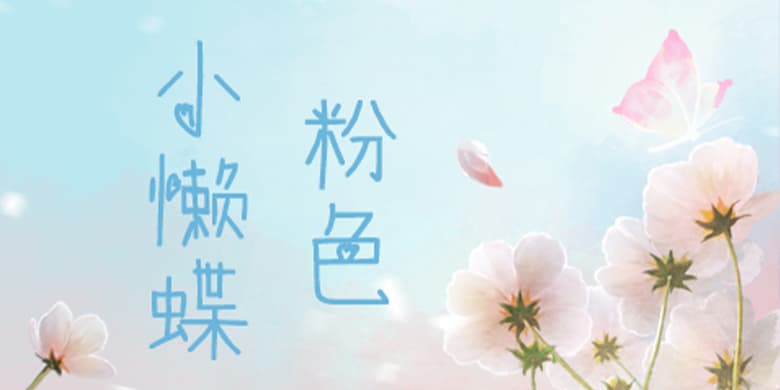
方正手迹-粉色小懒蝶
品牌:方正手迹设计师:郑海涛发行时间:2020字库编码:大陆简体(GB2312-80)分类:创意书写字体属性:精品字
方正手迹-粉色小懒蝶
粉色小懒蝶体,慵懒可爱的字形,点缀蝴蝶翅膀的简笔画元素,给人感觉轻松惬意,烂漫舒适。适用于少年儿童类的书刊、品牌广告和产品包装设计,综艺漫画用字,以及社交网络的个性化用字。